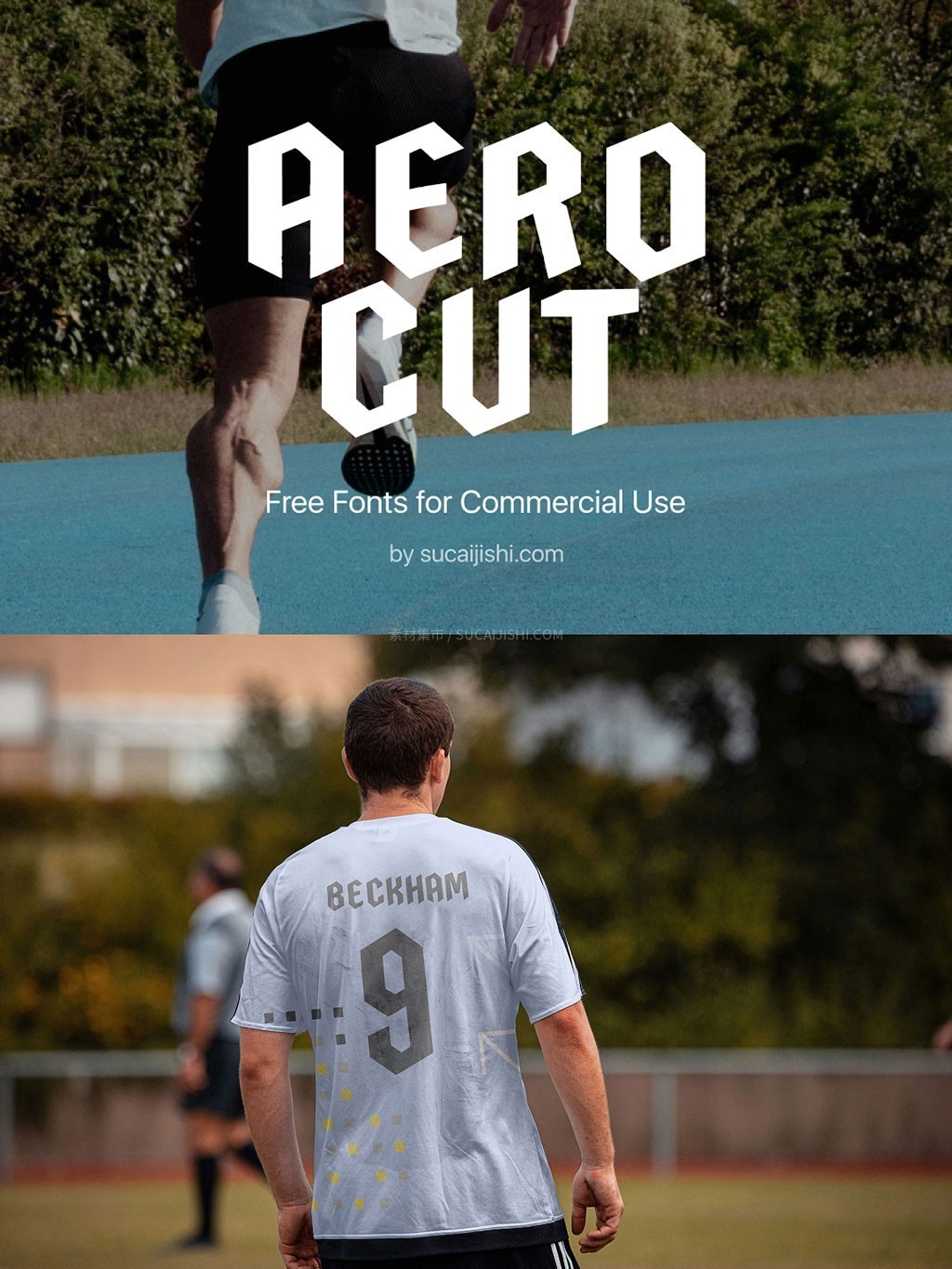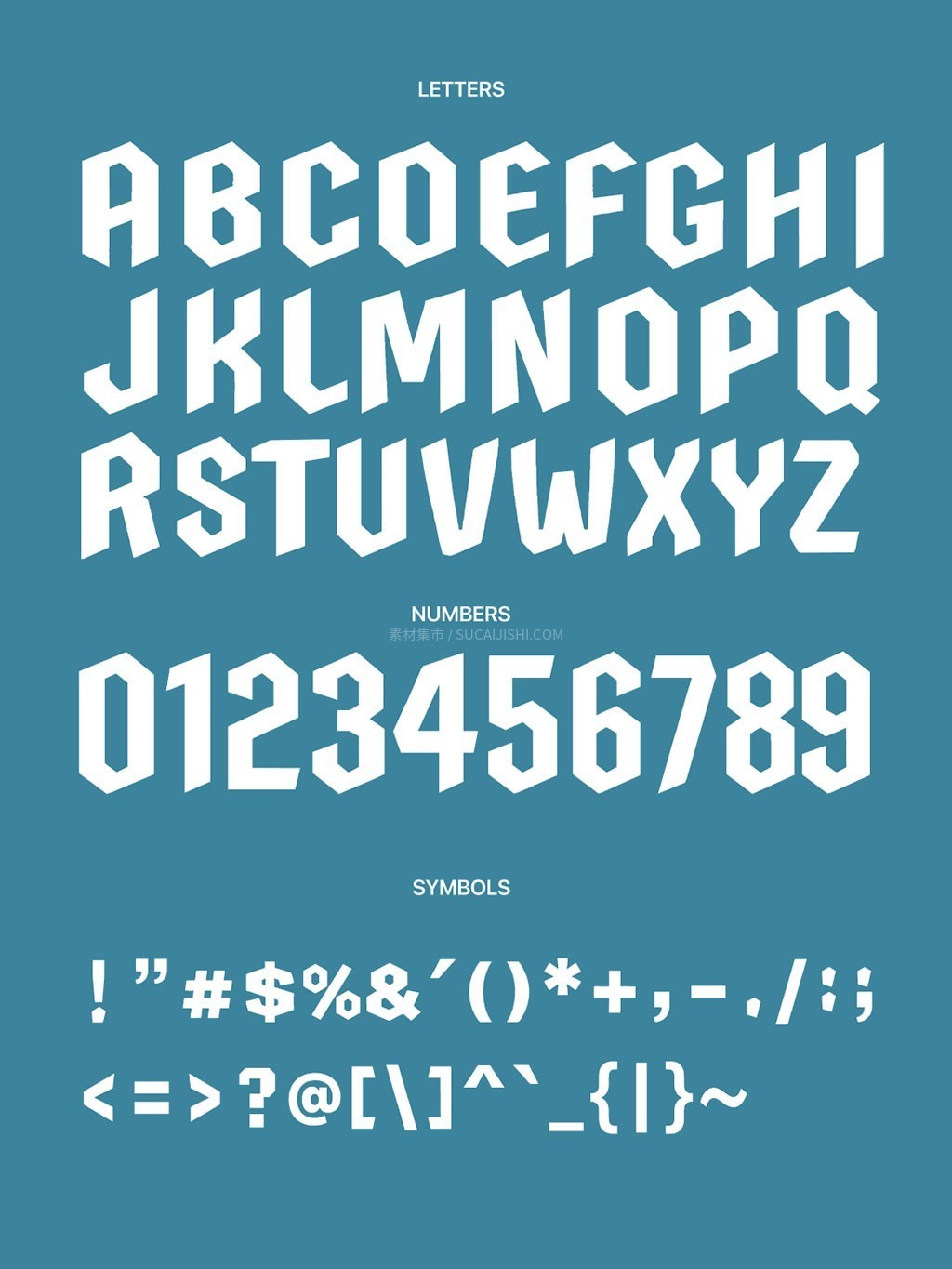
Sucaijishi Aero Cut 免费商用英文运动字体
一款极具侵略性和工业感的几何运动字体。它的核心视觉特征在于所有圆弧都被硬朗的直线和尖锐的斜切所取代,形成了一种坚如磐石的块状感。这种风格完美呼应了橄榄球、复古篮球球衣号码和赛车标志的坚韧感与速度感,是打造强视觉冲击力运动品牌LOGO的首选。
Sucaijishi Aero Cut 免费商用英文运动字体